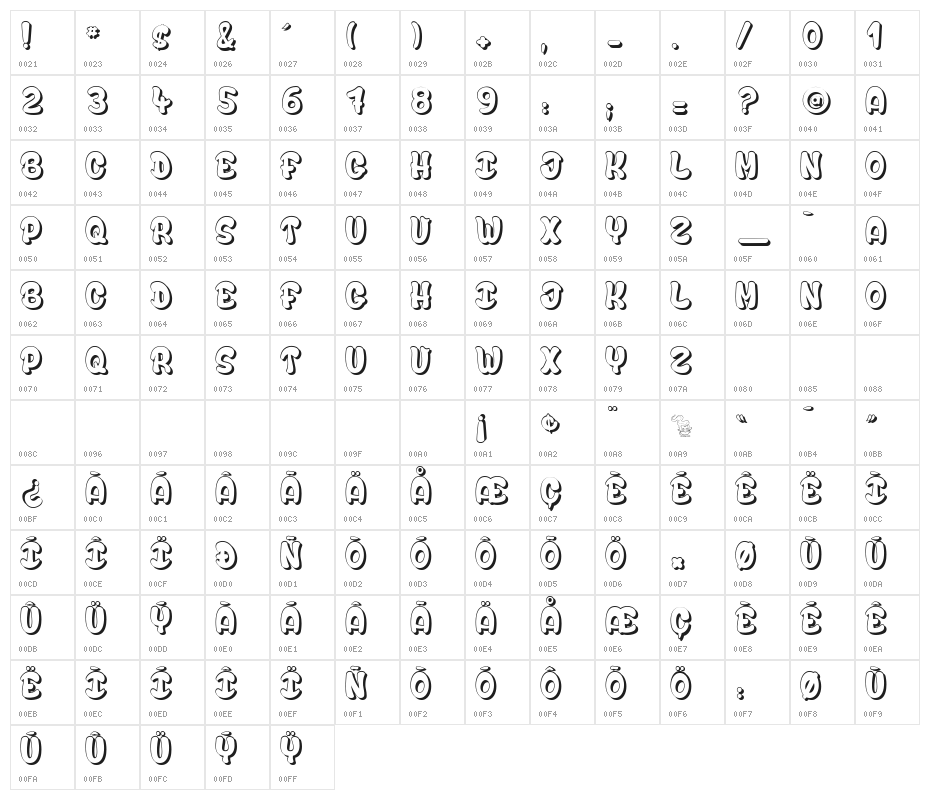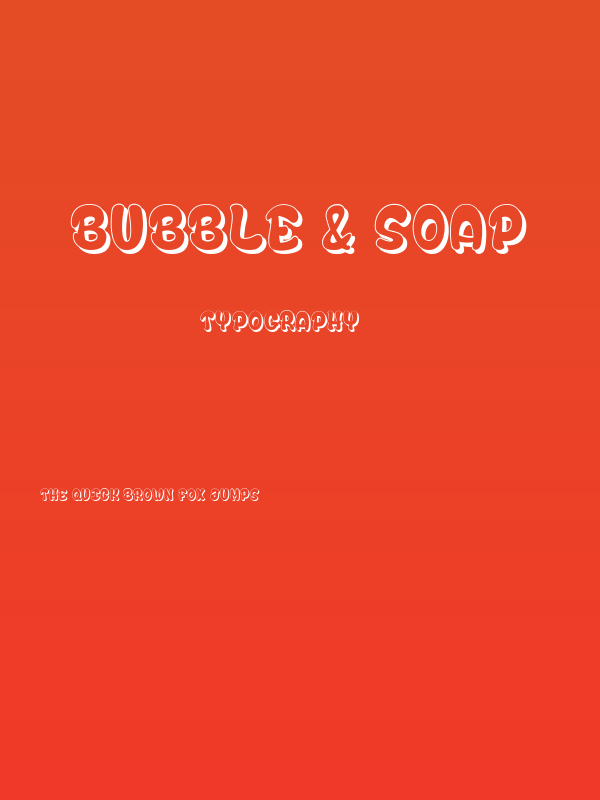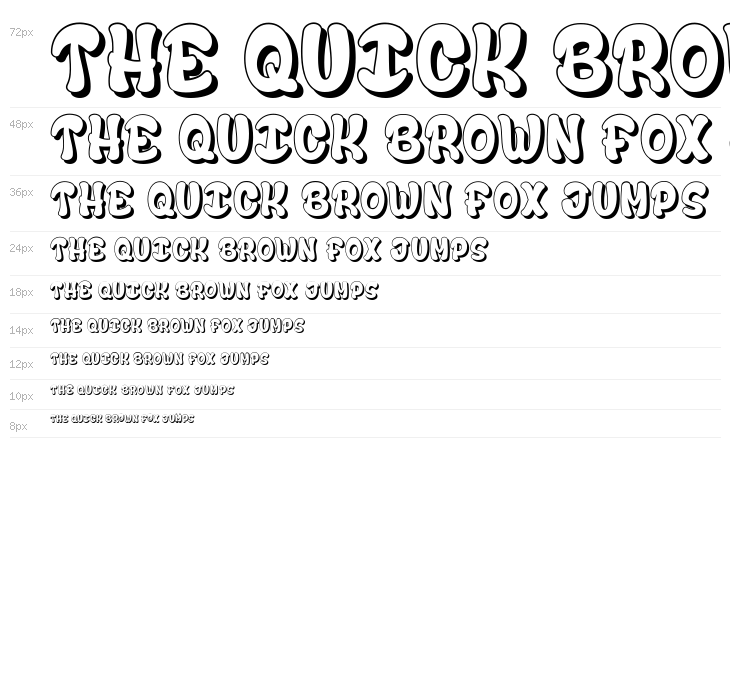
bubble & soap Font
| 整体风格 | Playful, Fun, Whimsical |
| 推荐项目 | Ideal for children's books, comic strips, playful branding, party invitations, and any project that requires a fun and lively touch. |